Hola amigos de Lettering Time, hace mas de un años os enseñábamos los trabajos del estudio I Love Dust y hace unas semanas os hablábamos de sus últimos trabajos a través de nuestra pagina en Facebook. Pues bien he tenido el placer de poder realizarles una interesante entrevista donde vamos a poder conocer mas sobre este brillante estudio, su manera de trabajar y sus clientes.
1- Empecemos por el principio, ¿Como llegas al mundo de la ilustraciĂłn y como nace I Love Dust?
Empecemos hace 11 años en un sĂłtano polvoriento asumiendo cualquier trabajo que podiamos. nuestro objetivo era trabajar de los que nos gustaba hacer y estar orgullosos de ello, y esto sigue siendo fundamental en la forma que tenemos de trabajar hoy en dĂa.
(En la actualidad cuentan con un fantástico estudio en Portsmouth)
2- ¿Como definirĂas tu trabajo?
Nosotros solo buscamos crear trabajos que nos emocionen, constantemente incorporamos caras nuevas e ideas para mantener la mente fresca y siempre miramos hacia adelante en vez de descansar en los éxitos del pasado.
3- ¿Que es lo que te inspira a la hora de realizar una nueva ilustraciĂłn?
Nada y todo. La inspiraciĂłn es el proyecto de la compasiĂłn, nosotros intentamos vivir lo que hacemos de una manera fuerte y sintiendo que la pasiĂłn esta reflejada en el proyecto.
4- Hace unos meses estuve en Barcelona y en la tienda oficial de Nike en el Camp Nou vi vuestro trabajo a en gran formato. Me quede impresionado por la cantidad de detalles que tenia la ilustracion y no dude en hacerle muchisimas fotos.
¿Podrias contarnos mas sobre este proyecto, como nacio y como se llevo a cabo?
Muy amable. Este realmente fue un fantástico proyecto en el que trabajar. Tenemos una gran relaciĂłn con Nike y nos une la pasiĂłn por fĂştbol asĂ que decidimos que estas ilustraciones iban a estar basadas fuertemente en la artesanĂa y en los detalles.
Dibujemos a mano todos los elementos de las mas de 30 ilustraciones de los diferentes equipos que Nike es sponsor.
5- I Love Dust trabaja para clientes de tanto renombre como Nike, Red Bull o MTV ¿Como llega I Love Dust a trabajar con ellos y como es trabajar con ellos?
Creo que en mucha medida el ser capaces de trabajar con grandes clientes se debe al maldito y duro trabajo, al hecho de entregar un producto de calidad a tiempo y dentro del presupuesto.
6- Vuestro proyectos ademas de unas maravillosas ilustraciones tambiĂ©n poseen una pesada carga de tipografĂa ¿Como de importante consideras la tipografĂa en vuestros trabajos?
La tipo siempre ha sido una caracterĂstica de lo que hacemos. Nos encanta lo expresiva que puede ser y los diferentes caminos que se pueden tomar con ella.
7- Vuestro trabajo es seguido por miles de seguidores en las mejores redes de creativos como Behance ¿Como de importantes creĂ©is que han sido estas en la difusiĂłn de vuestro trabajo?
Las redes sociales son una herramienta muy importante en esta industria hoy en dĂa. Podemos subir un trabajo por la mañana y por la tarde haber sido visto por miles de personas en todo el mundo y que nos contacte cualquier para para trabajar en nuevos proyectos o que nos pida el cliente que lo bajemos por que hemos incumplido algĂşn tipo de regla.
8- ¿Hacia donde va I Love Dust y que esperáis del futuro?
Nosotros buscamos constantemente ir hacia adelante y empujar nuestro trabajo hacia nuevas direcciones con descaro y sin ningĂşn tipo de jodidos complejos.
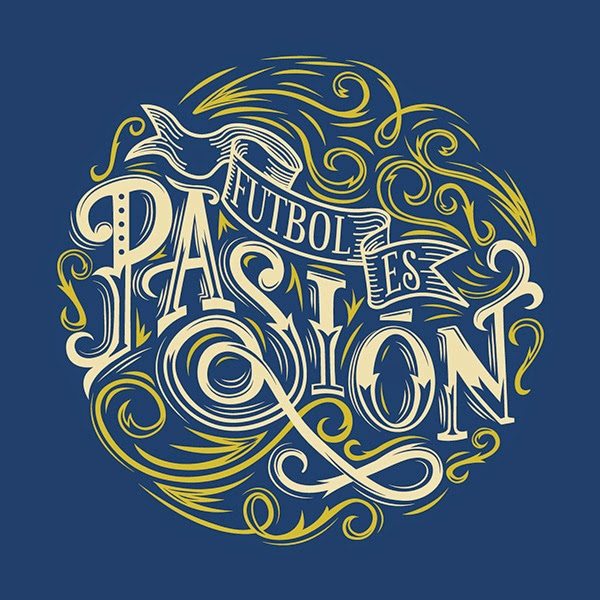
9- Por ultimo, ¿Que le recomendarĂais a alguien que esta empezando en el mundo del diseño y la ilustraciĂłn?
Trabajo duro. Hay que aconstumbrarse al cafe, a trasnochar y empezar temprano de nuevo a trabajar.